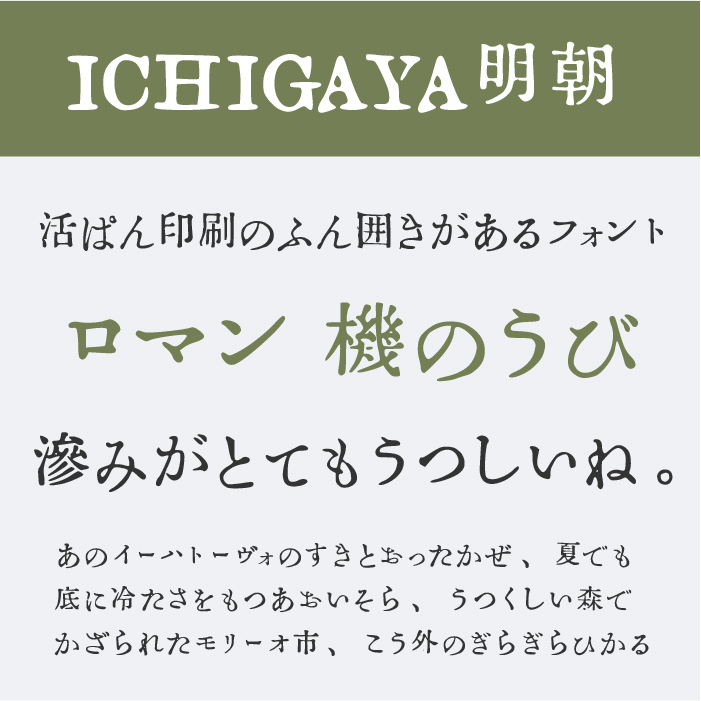
「活版印刷」な雰囲気がある日本語フリーフォント
今回は、大正・明治時代に主流であった印刷手法である「活版印刷」な雰囲気がある日本語フリーフォントフォントをまとめてみました。
現代の印刷では「活版印刷」はほぼ無くなってしまいましたが、一部の印刷会社では取り扱っているようですね。活版印刷は、インクのにじみやかすれなどの質感があることで、クラフト感・手作り感を感じるため、ぬくもりを感じさせてくれます。
今回は、そのような「活版印刷」をフォント上で表現した「活字印刷」な雰囲気がある日本語フリーフォントをご紹介します。
「活版印刷」の日本語フリーフォント
以下の画像サンプルは、本記事で紹介している「活版印刷」フォントの一部です。本記事のフォントを使うことで、このような「活版印刷」の雰囲気を表現することができるとってもステキなフォントです。
「活版印刷」の日本語フリーフォント
大正活字っぽい?
大正活字っぽい
大正活字っぽい?フォントT5は、大正時代の活字を再現したレトロな味わいがあるフォントです。インクのにじみや版ズレなどがしっかりと表現されている部分が渋いですね。
Oradana明朝
Oradano明朝フォントは、「活字の格好よさの源泉を考える材料」をコンセプトに、東京築地活版製造所が販売している見本を参考にしながら制作された明朝体フォントです。
GL-築地五号
築地5号
築地5号フォントは、東京築地活版製造所の活版見本をヒントにしながら制作されたフォントです。
大正略字
大正略字フォントは、上記でも紹介している「Oradana明朝」と「大正活字っぽい?フォント」を混植させベースにつつ、一部の漢字を略字に置き換えているフォントです。
文字の輪郭がインクがかすれているような質感にリアリティがあり、活字のカッコよい表現がフォントで再現されているフォントです。
XANO明朝
XANO明朝フォントは、活版印刷時代の活字のような味わいとレトロさがあるヴィンテージ風な明朝体フォントです。
ひな明朝
ひな明朝フォントは、文字の交差している部分などに墨のにじみや墨だまりがあり「伝統感」と「品」を感じることができる文字になっています。
ニューテゴミン
ニューテゴミン(New Tegomin)フォントは、インクのにじみや優しい雰囲気のオールドスタイル明朝体で手書き+明朝体のようなフォントになります。
ICHIGAYA明朝体
ICHIGAYA明朝体フォントは、秀英舎活版製造所の活字をベースに制作された明朝体フォントです。